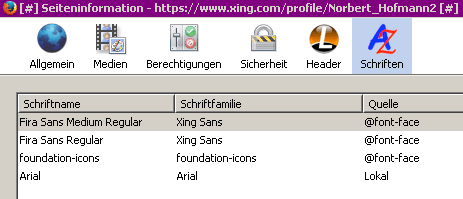
Xing hat neuen Corporate Font - Ich finde ihn schrecklich - Berechtigt?
1. 1. Wie findet ihr den neuen Corporate Font bei Xing?
• Es ist eine schöne Schrift aber für eine Online-Community nicht geeignet
• Es ist eine schöne Schrift, die sich sehr für eine Online-Community eignet
• Ich mag die Schrift nicht und sie passt auch nicht für eine Online-Community
• Ich mag die Schrift nicht, dennoch ist sie für eine Online-Community geeignet
Seit Kurzem hat Xing einen neuen Corporate Font.
Die Schrift ist für mich eine Zumutung und ich bin deshalb mit einem Browser Plug-in zur alten Schrift zurückgekehrt.
Wie findet ihr sie?
P.S. Die Powernutzer von Xing finden die Änderung eindeutig negativ:
Was sagt ihr Experten dazu?
Tatsächlich. Ich hatte erst eine (für XING modifizierte?) FF Meta vermutet, aber beim Einstellen der Beispiele kleine Unterschiede gesehen, die tatsächlich eher für die Fira zu sprechen scheinen. Hmm, im CSS wird sie als »Xing Sans« verkauft.
Ja, es ist Fira Sans!
Ich möchte Ihnen auf diesem Weg erläutern, weshalb wir uns für den neuen Font „Fira Sans“ entschieden haben und was die nächsten Schritte sind.
Wie jede Firma arbeiten auch wir kontinuierlich an der Verbesserung von Useability und Design. Ein Schritt in diesem Prozess ist die neue Font.
Wieso haben wir uns speziell für die „Fira Sans“ entschieden?
Es ist eine „digitale Schriftart“, basierend auf der Meta-Schriftart, die von dem deutschen Typografen Erik Spiekermann entwickelt wurde. Sie funktioniert auf allen mobilen Endgeräten, responsive Webdesigns, sowie auf größeren Displays.
Unser Meinungsformat XING Klartext https://www.xing.com/news/klartext beispielsweise ist direkt mit dieser Font vor sechs Monaten im Oktober gestartet. Diesen Zeitraum haben wir als Testphase vor der Implementierung auf der Plattform genutzt. Hier kam keinerlei negatives Feedback von unseren Mitgliedern (XING Klartext hat Stand Februar 2016 über eine Million Zugriffe). Aus diesem Grund haben wir uns für den nächsten Schritt, den Übergang auf die gesamte Plattform entschieden.
Dass es hier bei einigen Mitgliedern zu Darstellungsproblemen kam, bedauern wir sehr und wir sind uns bewusst, dass hier noch Optimierungsbedarf besteht. Hierzu zählt auch die Vergrößerung der Schriftart, der Zeilenabstand und Lesbarkeit angeht.
Unsere Priorität liegt nun in der Behebung signifikanter Probleme, welche wir durch Ihr Feedback evaluiert haben. Wir hoffen jedoch, dass Sie im Laufe der Zeit mit dem neuen Design vertraut werden.
Ich bin nicht bei XING... Wie sah das denn vorher aus bzw. welche Schriftart wurde denn vorher benutzt?
A) Es ist eine schöne Schrift aber für eine Online-Community nicht geeignet
B) Es ist eine schöne Schrift, die sich sehr für eine Online-Community eignet
C) Ich mag die Schrift nicht und sie passt auch nicht für eine Online-Community
D) Ich mag die Schrift nicht, dennoch ist sie für eine Online-Community geeignet
E) Die Schrift ist in Ordnung, aber man kann sie in einem feststehenden Webdesign nicht einfach als Ersatz für eine Systemschrift benutzen ohne die Schriftsatz- und Design-Parameter entsprechend anzupassen. Wenn die Schrift als schlecht lesbar empfunden wird, ist sie wohl einfach zu klein gesetzt.
Ihr habt recht es ist die Fira Sans.
Am Windooffon sieht alles nach Arial aus.
Das wird Erik Spiekermann aber gar nicht gefallen, daß seine Schrift wie die Arial aussieht. Aber möglicherweise wird wirklich die Arial angezeigt, denn aus irgendwelchen Gründen wird die Fira Sans nur angezeigt wen JavaScript aktiviert ist. Ansonsten bekommt man statt dessen die Arial zu sehen.
Warum man dies hier so macht ist mir nicht ganz verständlich. Normalerweise versuchen so etwas paranoide Schriftanbieter zu verhindern, daß man sich den Webfont angelt. Aber bei einem Freefont?